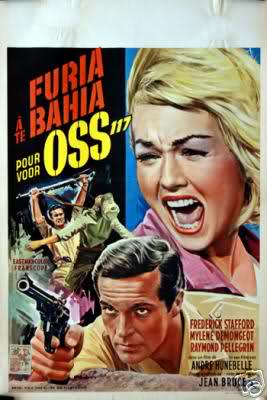
Vertikal "halbierte" Schrift eines Filmplakates 60er J.
Für die Gestaltung eines DVD-Covers soll die Schrift "OSS" nachgebaut werden. Hat jemand von Euch eine Ahnung, um was für einen Font es sich handeln könnte?